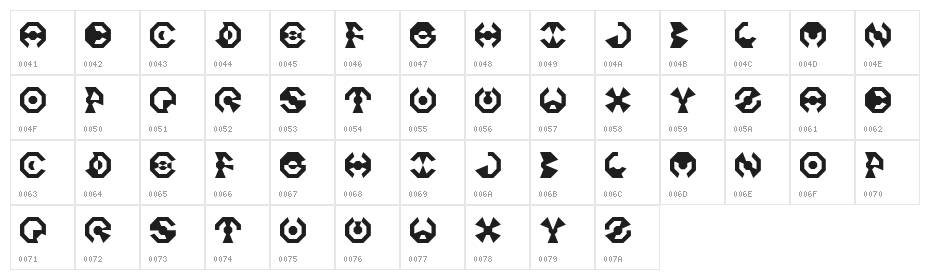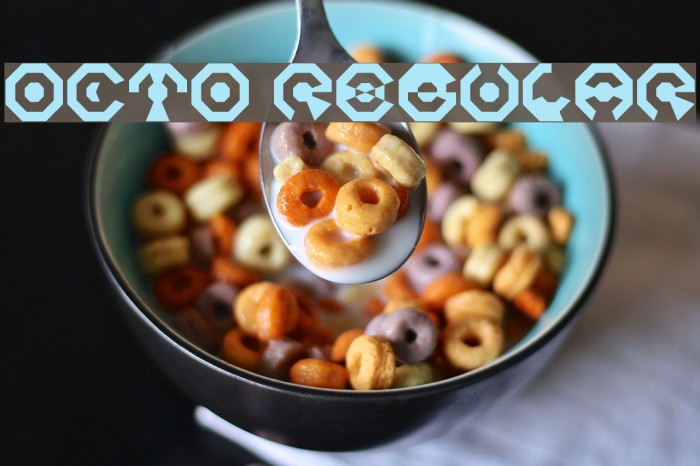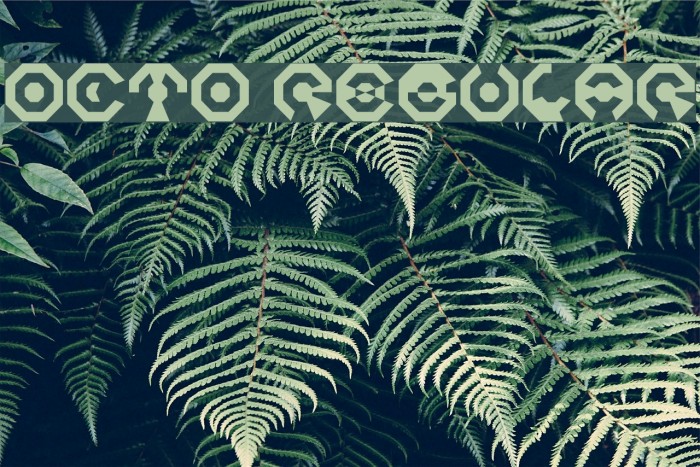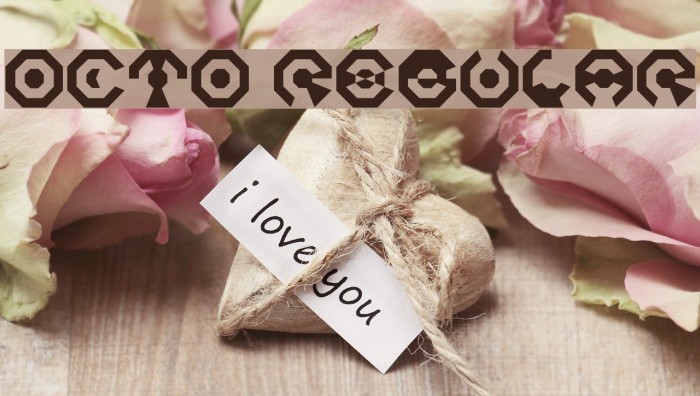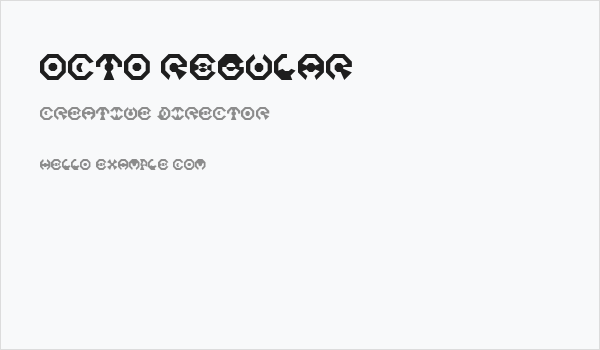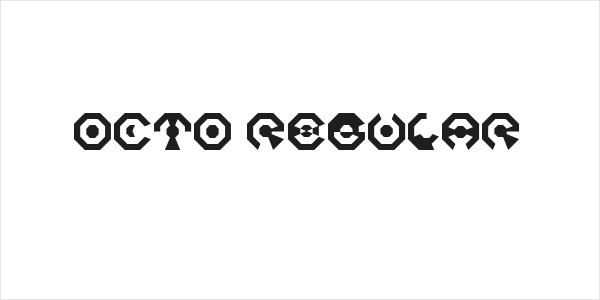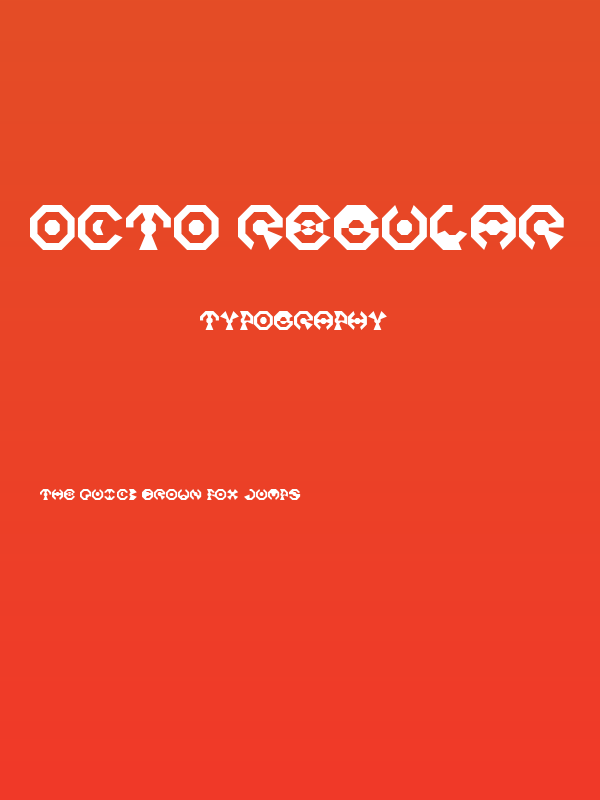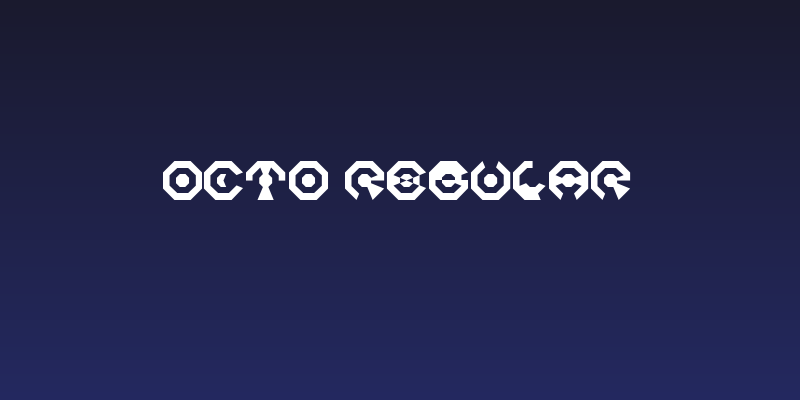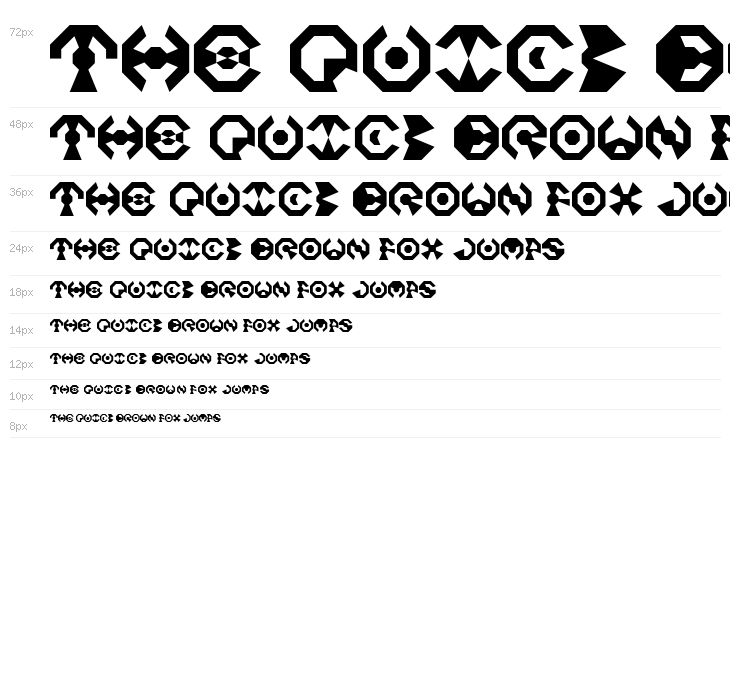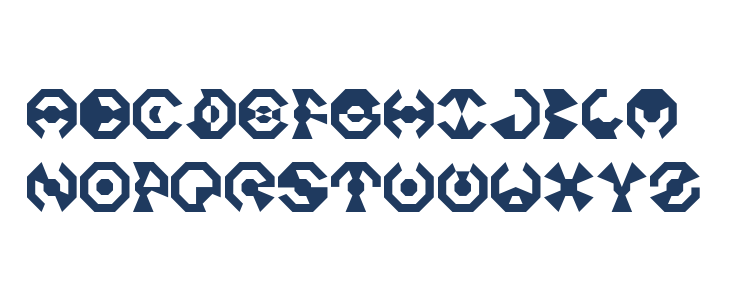
Octo Regular Font
| Stile generale | Futuristic |
| Caso d'uso | Logos, Headlines |
| Progetti proposti | Ideal for tech branding, video game titles, and futuristic posters. |